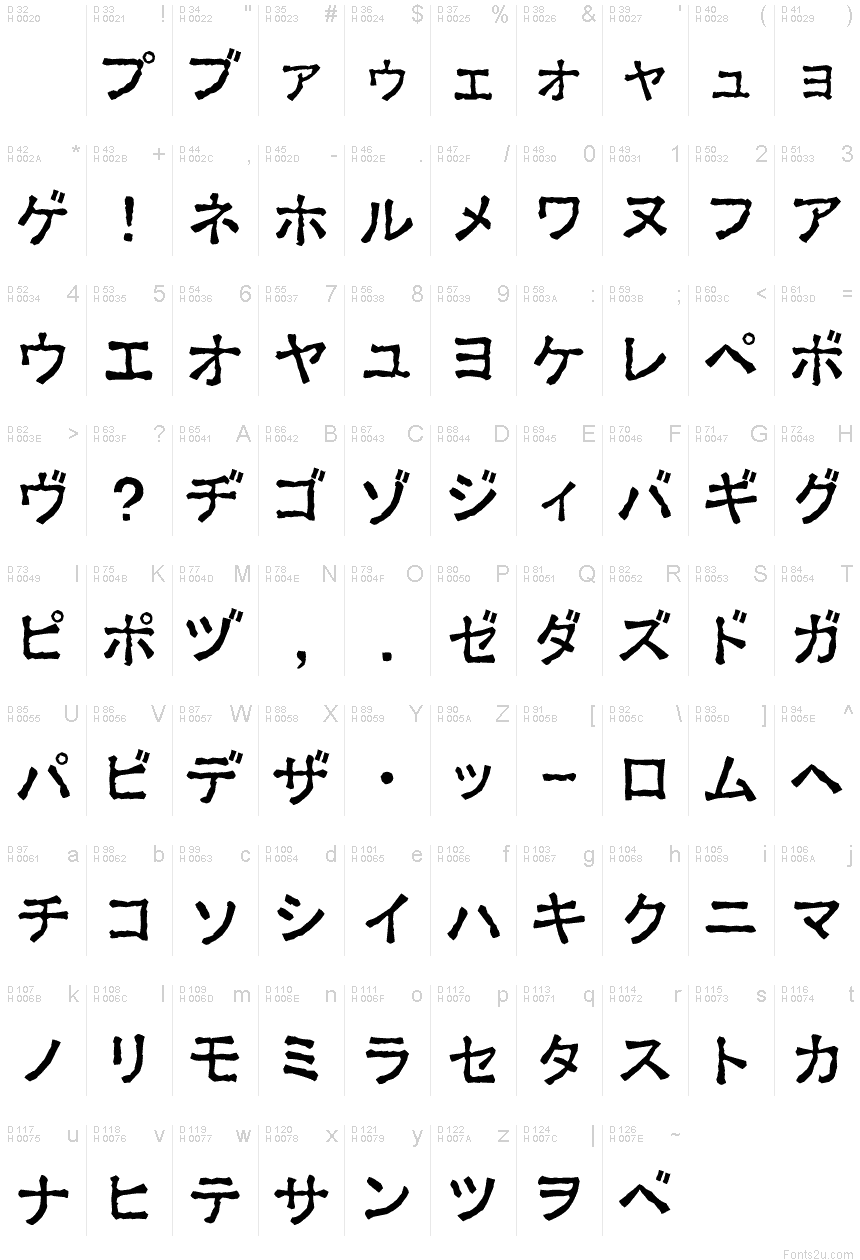
Ex Kata Opaque von Vic Fieger ist eine kostenlose, japanisch inspirierte Pinselschrift mit einer kräftigen, tintenartigen Präsenz. Die Striche wirken wie mit einem leicht ausgefransten Pinsel gemalt – deckend schwarz, mit rauen Kanten, die sich handgemacht anfühlen. Die Buchstaben bleiben gut lesbar und bewahren dabei den unregelmäßigen, organischen Rhythmus, den man von schneller kalligrafischer Beschriftung auf Papier oder Holz erwartet.
Mit Ex Kata Opaque gewinnen Überschriften sofort an Fokus und erhalten eine cineastische, japanisch angehauchte Stimmung. Dies funktioniert wunderbar für Poster, Ramen- oder Sushi-Branding, Indie-Comics, Zines, Verpackungen und Event-Flyer. Diese kostenlose Schrift glänzt besonders in großen Formaten, wo ihre texturierten Kanten richtig zur Geltung kommen. Kombinieren Sie sie mit einer klaren, geometrischen serifenlosen Schrift im Fließtext, um ein ausgewogenes und lesbares Layout zu wahren, während Ex Kata Opaque die ausdrucksstarke Arbeit übernimmt.